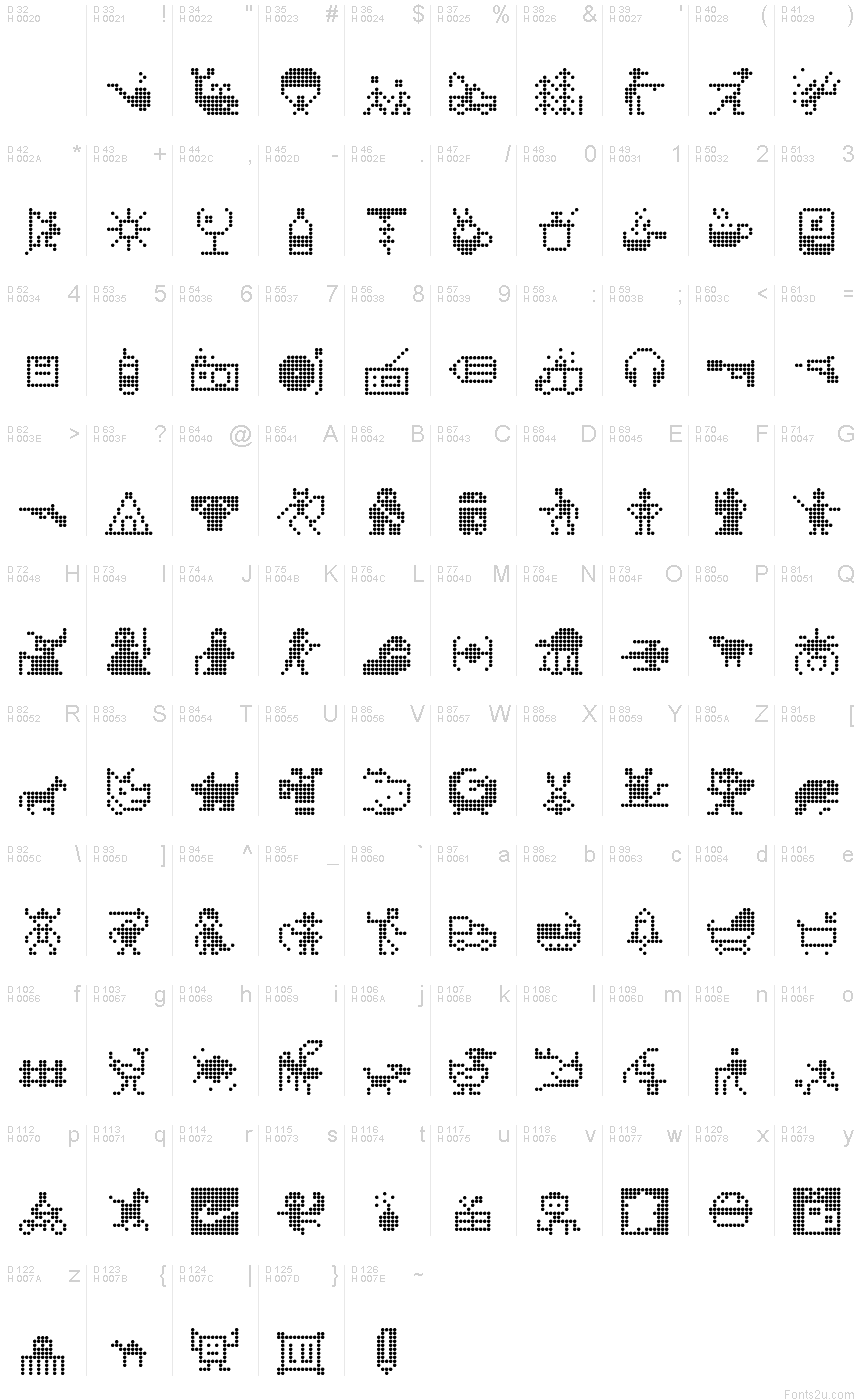
Signotek
Signotek od Trafik to darmowy font z piktogramami, który przekształca grafikę znaków publicznych w wyraźne pola równomiernie rozmieszczonych punktów. Stylistyka nawiązuje do systemów informacji wizualnej i ikonografii transportu – figurki pieszych, strzałki i zwarte symbole zostały zredukowane do modułowego, niemalże diodowego języka graficznego, który jest bezpośredni i przyjazny, a nie przesadnie wygładzony.
Sprawia to, że font naturalnie pasuje do map, oznaczeń imprezowych, markerów interfejsu, plakatów, opakowań i krótkich grafik redakcyjnych, gdzie prosty symbol jest czytany szybciej niż ilustracja. Jako darmowe pismo, doskonale sprawdza się również w napisach tytułowych, naklejkach i krótkich systemach etykiet, które wymagają spójnego, kropkowego motywu oraz czytelnego, miejskiego charakteru.